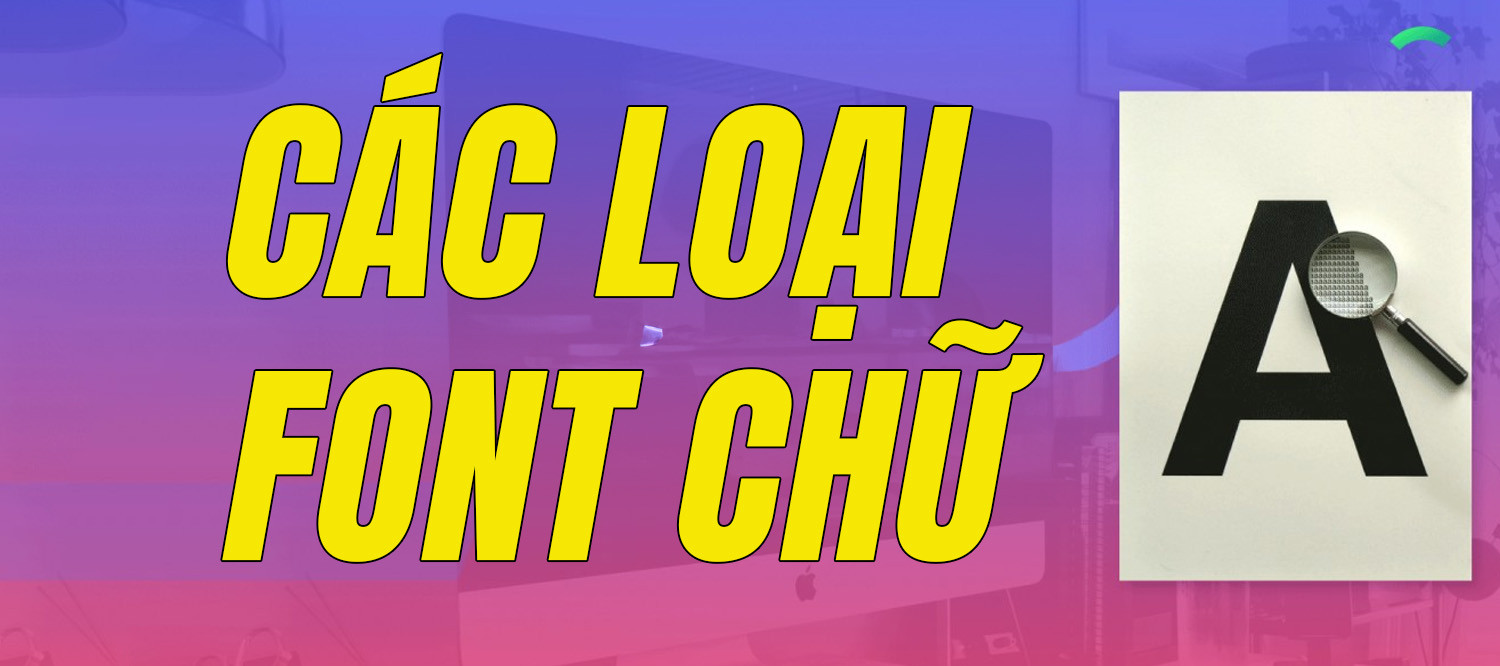
Font chữ đóng vai trò quan trọng trong thiết kế và truyền tải thông điệp. Hiện nay, có nhiều loại font chữ phổ biến, mỗi loại mang đặc điểm và ứng dụng riêng. Serif mang vẻ truyền thống và trang trọng, thường dùng trong sách và tài liệu in ấn. Sans-serif mang phong cách hiện đại, dễ đọc trên màn hình, lý tưởng cho web và ứng dụng di động. Script mô phỏng nét viết tay, tạo cảm giác sáng tạo và cá nhân. Display nổi bật và bắt mắt, phù hợp cho tiêu đề và quảng cáo. Monospaced có các ký tự đều nhau, dùng cho code và tài liệu kỹ thuật. Decorative và Handwritten mang tính nghệ thuật cao, thích hợp cho thiệp mời và thiết kế sáng tạo. Hãy cũng S99 tìm hiểu chi tiết đặc viểm và ứng dụng các loại font chữ nhé
Font chữ Serif là loại font chữ có các đường nét gạch nhỏ (serif) ở đầu và cuối mỗi ký tự, tạo nên vẻ đẹp truyền thống và trang trọng. Các font chữ Serif mang lại cảm giác tin cậy, ổn định và dễ đọc, đặc biệt là trong các văn bản dài. Đây là lý do tại sao chúng thường được sử dụng trong sách, báo, tạp chí và các tài liệu in ấn khác. Font chữ Serif giúp mắt người đọc dễ dàng di chuyển từ ký tự này sang ký tự khác, làm tăng trải nghiệm đọc mượt mà hơn.
Trong các lĩnh vực như luật pháp, tài chính và giáo dục, font chữ Serif thường được ưu tiên vì tính chuyên nghiệp và nghiêm túc mà chúng mang lại. Những font chữ nổi tiếng như Times New Roman, Georgia và Garamond là những ví dụ điển hình của font chữ Serif, thường xuất hiện trong các báo cáo, luận văn, và tài liệu học thuật.
Ngoài ra, font chữ Serif cũng được sử dụng trong các thiết kế đồ họa mang tính cổ điển và sang trọng. Thiết kế bao bì, thiệp mời và bìa sách cũng thường sử dụng font chữ Serif để tạo nên vẻ đẹp trang nhã và tinh tế. Sự kết hợp giữa tính thẩm mỹ cao và khả năng truyền tải thông điệp một cách rõ ràng, hiệu quả làm cho font chữ Serif trở thành một lựa chọn phổ biến và đáng tin cậy trong nhiều lĩnh vực thiết kế và xuất bản.
Font chữ Sans-serif là loại font chữ không có các đường nét gạch nhỏ (serif) ở đầu và cuối mỗi ký tự, mang lại vẻ đẹp đơn giản, hiện đại và sạch sẽ. Các font chữ Sans-serif thường dễ đọc trên màn hình kỹ thuật số và các thiết bị điện tử, nhờ vào các nét chữ rõ ràng và gọn gàng. Điều này làm cho chúng trở thành lựa chọn phổ biến trong thiết kế giao diện người dùng, trang web, ứng dụng di động và các tài liệu kỹ thuật số.
Font chữ Sans-serif thường được sử dụng trong các tài liệu kinh doanh, quảng cáo, và các ấn phẩm đòi hỏi tính chuyên nghiệp và hiện đại. Những font chữ nổi tiếng như Arial, Helvetica, và Calibri là những ví dụ điển hình của font chữ Sans-serif. Arial thường xuất hiện trong các tài liệu văn phòng và báo cáo, Helvetica được ưa chuộng trong thiết kế đồ họa và nhận diện thương hiệu, còn Calibri là font chữ mặc định trong nhiều phần mềm xử lý văn bản.
Ngoài ra, font chữ Sans-serif cũng thích hợp cho các thiết kế quảng cáo và tiếp thị nhờ vào khả năng thu hút sự chú ý của người đọc một cách nhanh chóng và hiệu quả. Các tiêu đề, khẩu hiệu, và thông tin quan trọng thường được trình bày bằng font chữ Sans-serif để đảm bảo tính rõ ràng và dễ đọc.
Font chữ Script là loại font chữ mô phỏng nét chữ viết tay, mang đến cảm giác mềm mại, tinh tế và cá nhân hóa. Với các đường nét liên kết uyển chuyển, font chữ này thường được sử dụng trong các thiết kế đòi hỏi sự độc đáo và nghệ thuật. Font chữ Script lý tưởng cho thiệp mời, thiệp cưới, bìa sách và poster sự kiện, giúp tạo nên không khí trang trọng và lãng mạn. Những font chữ như Brush Script, Pacifico và Lobster là ví dụ điển hình, mang lại vẻ đẹp sáng tạo và thân thiện cho các dự án thiết kế.
Font chữ Display là loại font chữ được thiết kế để tạo ấn tượng mạnh mẽ và thu hút sự chú ý ngay từ cái nhìn đầu tiên. Với các đường nét độc đáo, táo bạo và thường có kích thước lớn, font chữ Display mang lại vẻ đẹp bắt mắt và phong cách đặc trưng cho các thiết kế. Những font chữ này thường được sử dụng trong tiêu đề báo, poster, biển quảng cáo và các thiết kế đòi hỏi sự nổi bật.
Font chữ Display giúp truyền tải thông điệp một cách rõ ràng và mạnh mẽ, phù hợp cho các chiến dịch quảng cáo, sự kiện văn hóa và các dự án sáng tạo. Các ví dụ điển hình của font chữ Display bao gồm Impact, Bebas Neue và Futura Display, mang lại vẻ đẹp hiện đại và ấn tượng. Font chữ Display không chỉ tạo điểm nhấn thị giác mà còn góp phần làm cho thiết kế trở nên độc đáo và cuốn hút hơn, đảm bảo rằng thông điệp của bạn sẽ được ghi nhớ.
Font chữ Monospaced là loại font chữ có các ký tự đều nhau về chiều rộng, mỗi ký tự chiếm một không gian ngang bằng nhau, tạo ra một vẻ đẹp gọn gàng và rõ ràng. Đặc điểm này giúp font chữ Monospaced trở nên dễ đọc và chính xác, đặc biệt hữu ích trong các ngữ cảnh yêu cầu sự nhất quán về bố cục, như trong lập trình, bảng tính và tài liệu kỹ thuật.
Font chữ Monospaced thường mang lại cảm giác kỹ thuật và cổ điển, làm cho nó trở nên phổ biến trong các môi trường liên quan đến công nghệ và khoa học. Những ví dụ điển hình của font chữ Monospaced bao gồm Courier New, Consolas và Monaco, được ưa chuộng trong việc hiển thị mã nguồn, tài liệu hướng dẫn và các biểu đồ dữ liệu. Font chữ này không chỉ đảm bảo tính thẩm mỹ cao mà còn giúp duy trì sự rõ ràng và dễ đọc, đặc biệt trong các tài liệu yêu cầu độ chính xác và chi tiết cao.